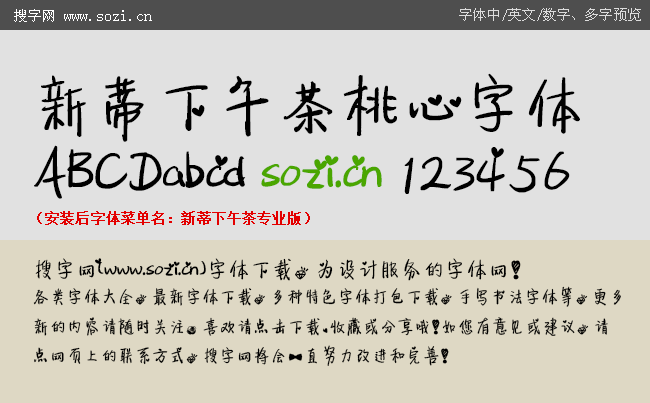
新蒂下午茶桃心字體
搜字網(wǎng)給大家提供一款書法風(fēng)格的字體下載。修改者給他起名為新蒂下午茶桃心字體,這款手機(jī)字體是以新蒂下午茶字體為原形,將字體的個(gè)別筆畫用心形圖案替換,新蒂下午茶字體是一款手寫風(fēng)格的中文簡體字體,非常有手寫感,一些筆畫替換卡通心形圖案后更加可愛,喜歡的朋友可下載收藏。